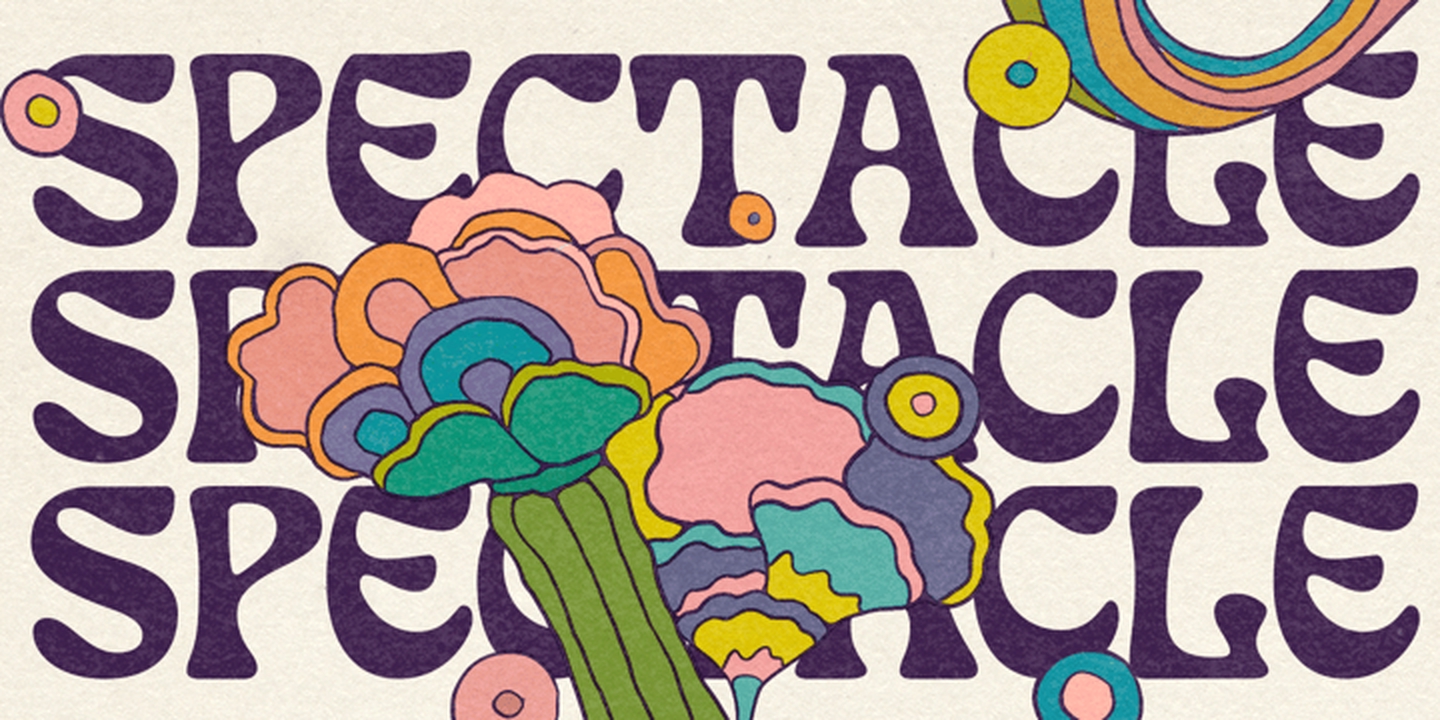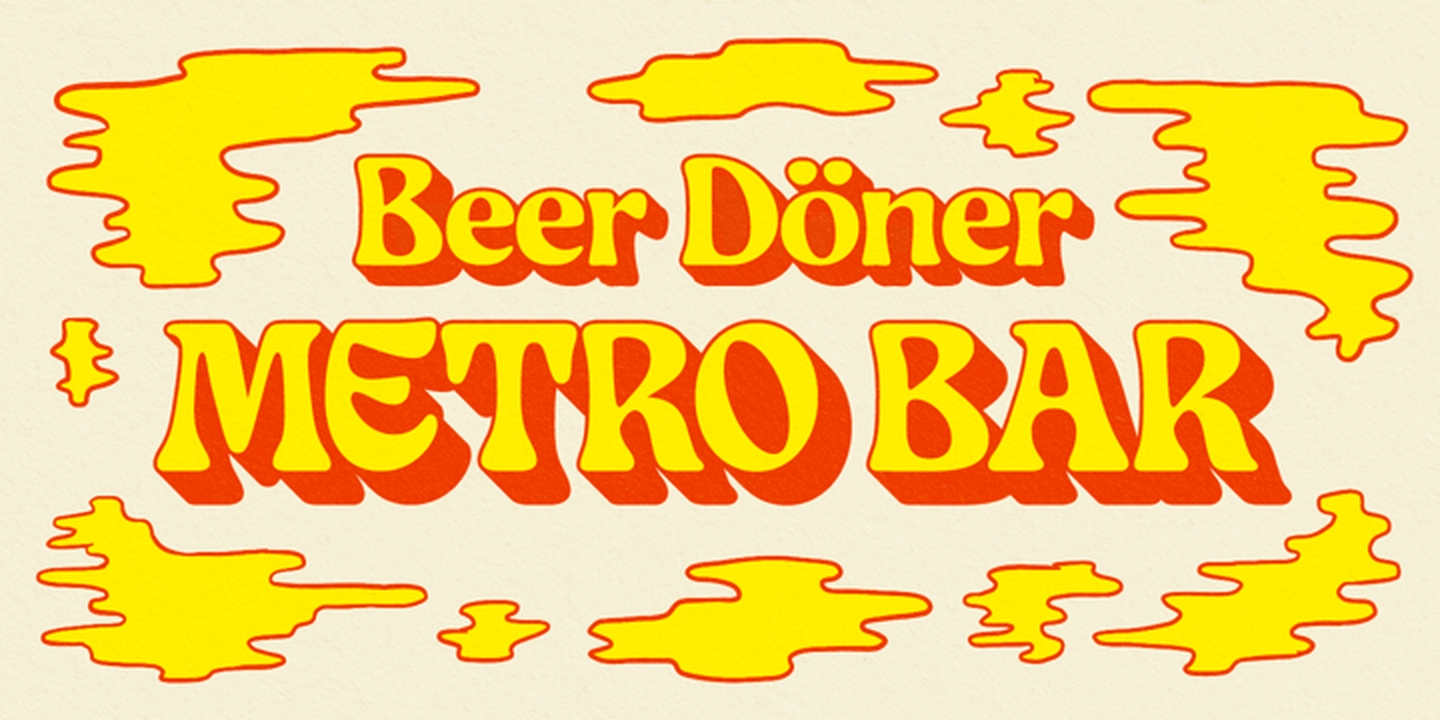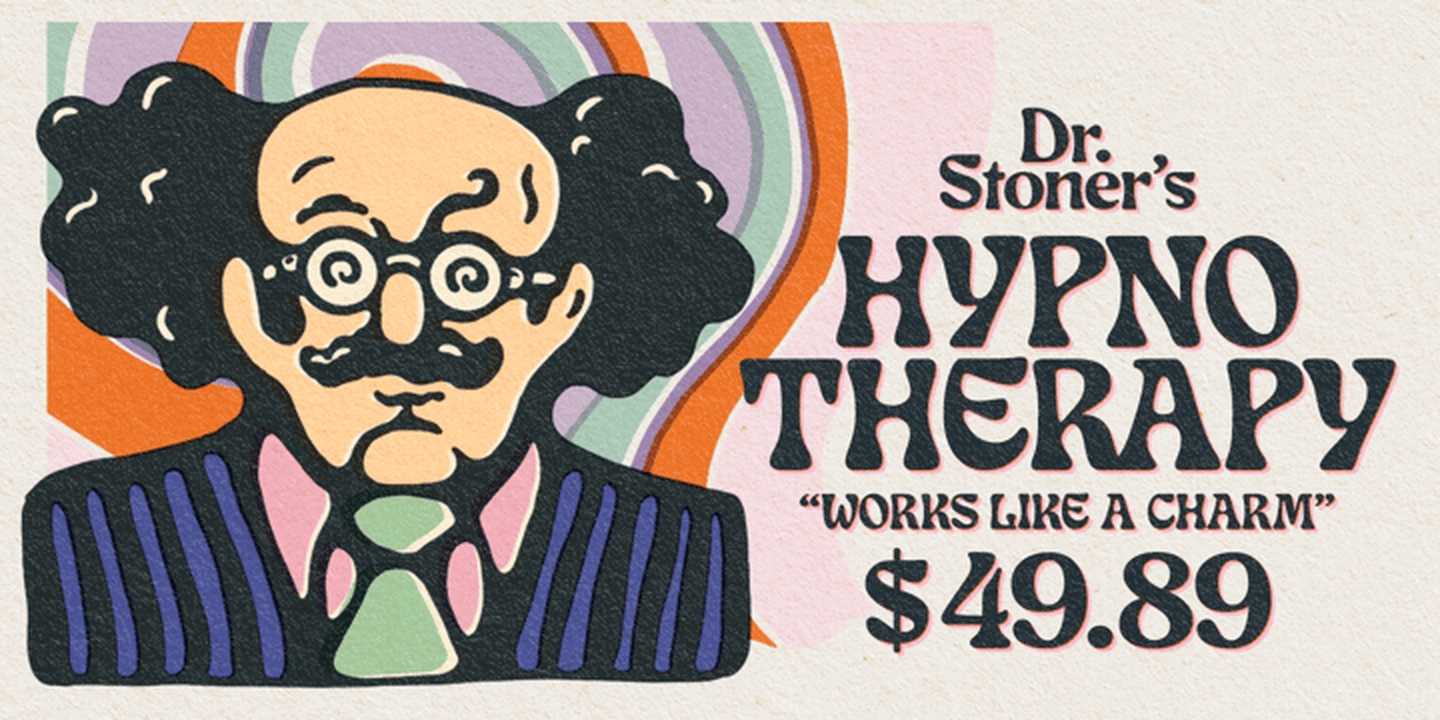
Love And Peace Font
Description de Love And Peace Font
Love and Peace est une police de style Art Nouveau de Penotype Foundry, qui s’inspire d’Eckmann-Schrift d’Otto Eckmann en 1900. La police est idéale pour les affiches de fête et les couvertures spécialement psychédéliques car elle donne un aspect similaire aux mots tordus. Il est doté de fonctionnalités intéressantes, notamment des alternatives contextuelles et des ligatures standard pour empêcher les caractères d’entrer en collision. De plus, il propose également des alternatives élégantes supplémentaires pour les minuscules a, k, r et s, ce qui rend vos créations superbes. Une autre caractéristique de cette police est l’ornement alternatif pour l’esperluette et le signe dollar. Cette police est disponible au format de fichier OTF.